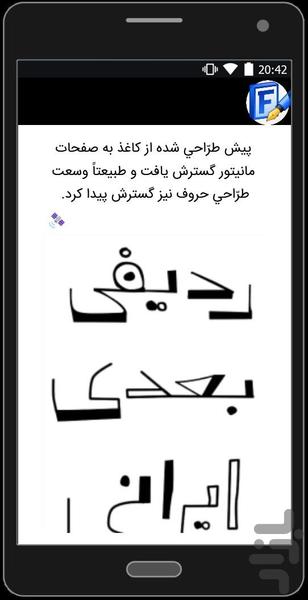
در اين اپلیکیشن سعي مي کنيم مراحل ساخت قلم را توضيح دهيم و براي ملموستر بودن آن، مراحل ساخت قلمِ
«رفاقت » را که براي استفاده در عنوان مطالب يک کتاب کودک _رفاقت با سازهاي ايراني ٣_ طّراحي شده به عنوان مثال خواهيم آورد.
البته هنرِ حروفنگاري و همچنين شيوهي کار با نرم افزارهاي طّراحي و ساخت قلم بسيار گستردهتر از آن است که بتوان در اين اپلیکیشن کوتاه به همه ي آن پرداخت اما اميدواريم خوانندگان با اپلیکیشن به اين موضوع علاقه مند شده، انگيزهي کار برروي قلم ها، ساخت و يا تغيير آنها مطابق با نيازشان را پيدا کنند.